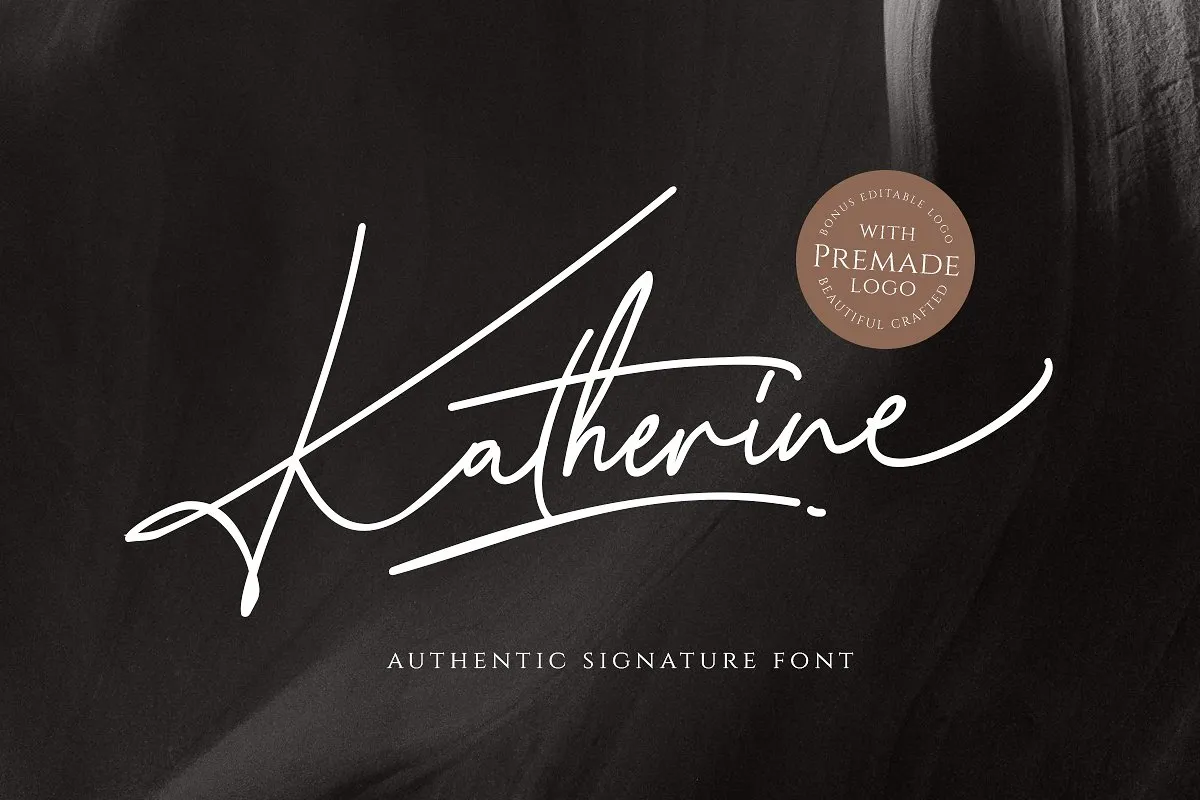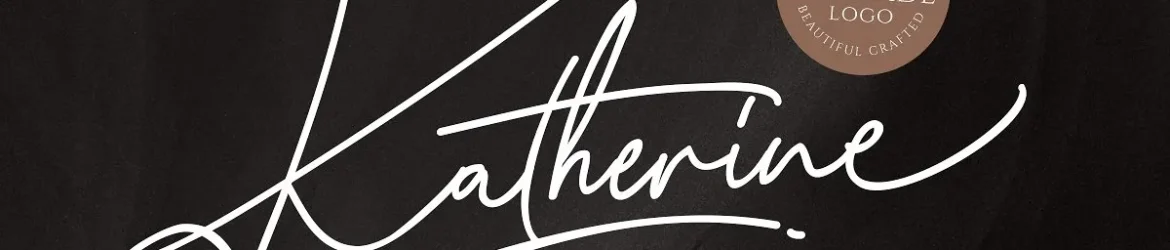
Katherine Signature Font – Download Grátis
Aqui está uma descrição em português para a página de download da font ‘Katherine Signature Font’, seguindo as regras fornecidas: Estamos entusiasmados em apresentar a fonte Katherine Signature, um design elegante e casual que traz uma atmosfera romanceada. Ideal tanto para assinaturas personalizadas quanto para gráficos de logomarcas modernos, essa fonte é perfeita para projetos de moda sofisticados, convites de casamento, ou até mesmo citações manuscritas em estilo elegante. Katherine Signature é uma autêntica opção para quem busca um toque romântico e sofisticado. Com suporte a letras maiúsculas e minúsculas, símbolos e suporte a múltiplas línguas, essa fonte traz elegância e charme às criações digitais. O design delicado da Katherine Signature se torna perfeito para projetos que exigem uma sensação de sofisticação e romance. Com um visual atraente e versátil, essa fonte é o item ideal para aqueles buscando trazer um toque especial aos seus trabalhos de design gráfico. Seja em letras digitais ou manuscritas, Katherine Signature garante que seu trabalho seja reconhecido com precisão e elegância. Aproveite a oportunidade de trazer sua assinatura personalizada ao topo das suas criações, usando a arte da fonte Katherine para dar um toque autêntico e inconfundível à sua identidade visual.